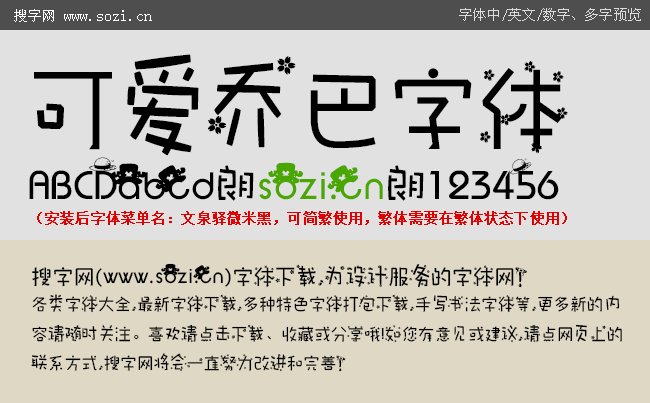
可愛喬巴字體
搜字網(wǎng)給大家提供一款很可愛的手寫風(fēng)格手機(jī)中文字體下載。修改者將它命名為可愛喬巴字體,這款手機(jī)字體是將文泉驛微米黑體的字體風(fēng)格進(jìn)行了卡通變化。并插入了一些可愛的卡通圖案,將端正的黑體變成了一款非常可愛的兒童卡通字體,特別適合小朋友和擁有可愛童心的朋友在手機(jī)上安裝使用。